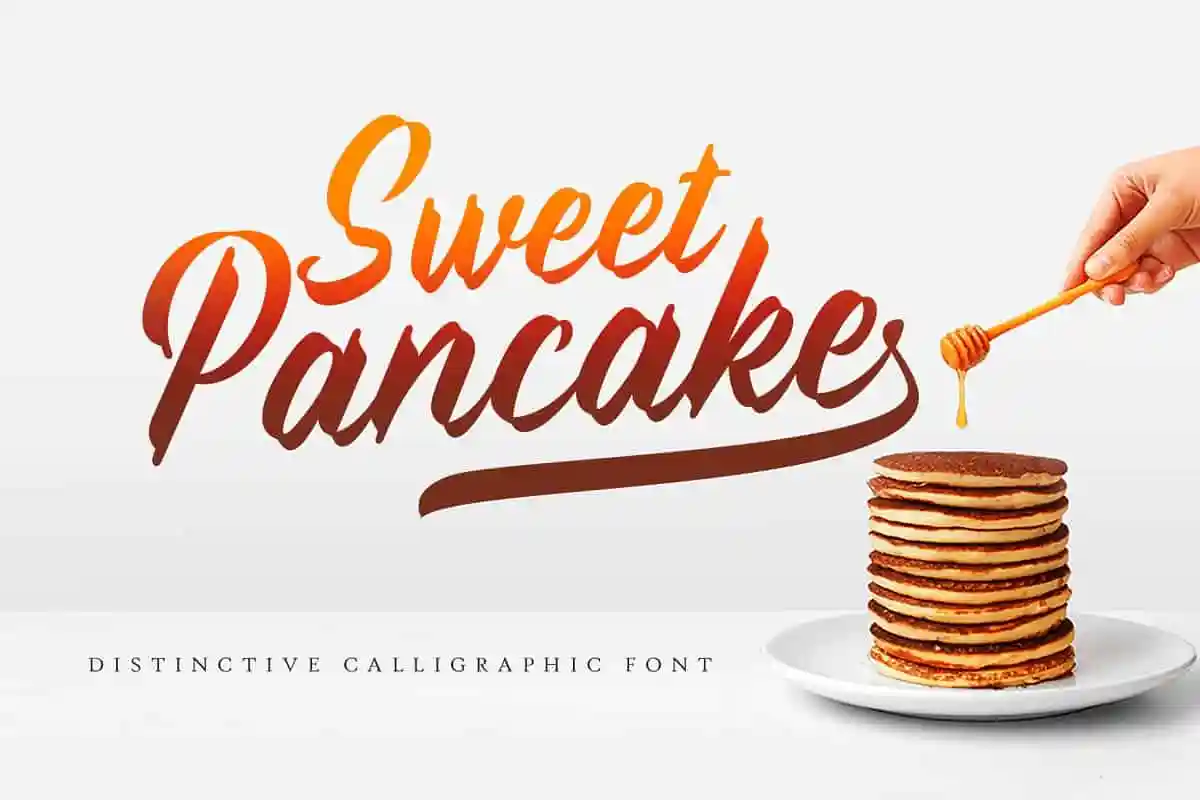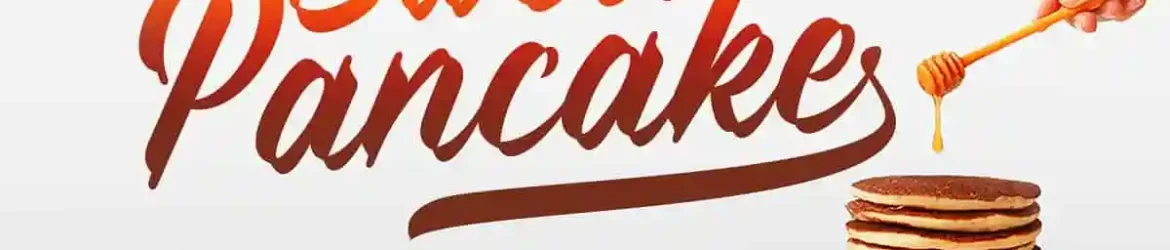
Sweet Pancake Script Font – Download Grátis
A Sweet Pancake Script Font é uma nova fonte moderna para escrita com estilo apresentada pelo designer Locomotype através do 178-MC. Esta fonte vem numa variedade de estilos de caligrafia, adaptando o seu padrão base para um visual mais pessoal e especial. A Sweet Pancake Script Font é perfeitamente adequada para logotipos, convites, outdoors e muito mais. Disponível tanto em formato OTF como TTF, a fonte também suporta múltiplas línguas e codificação PUA (Unicode), tornando-a uma opção versátil e pronta para o uso. Uma escolha ideal para designers gráficos que buscam um toque descontraído e único em seus projetos.